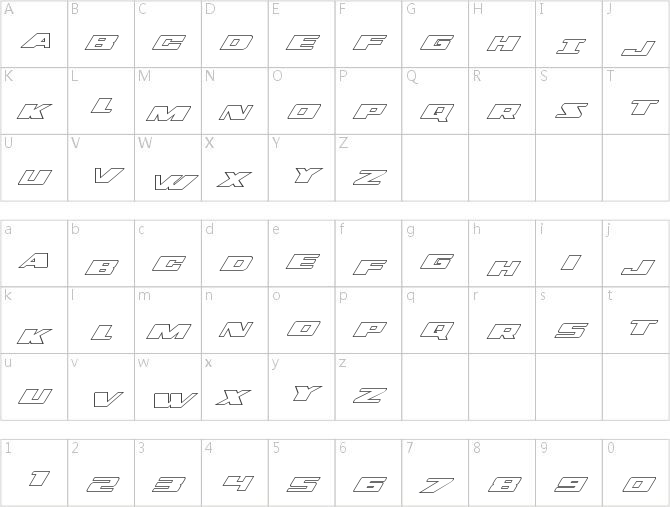
Dassault Outline Italic
Dassault Outline Italic介紹
Dassault Outline Italic字體字庫是一款讓人賞心悅目、百看不厭的英文字體,適合各類廣告和產品包裝設計應用,字體大小0.06MB,格式為ttf字體,上傳用戶是哼哼哈兮,作者/版權方為未知